Font chữ trung quốc việt hóa là một trong những công cụ không thể thiếu đối với các nhà thiết kế, dân văn phòng, hay đơn giản là những ai yêu thích phong cách chữ viết tay Trung Hoa. Với sự phát triển mạnh mẽ của công nghệ, việc tìm kiếm và sử dụng các font chữ Trung Quốc đã trở nên dễ dàng hơn bao giờ hết. Tuy nhiên, không phải ai cũng biết cách chọn font phù hợp, hay cách cài đặt một cách hiệu quả. Bài viết này sẽ cung cấp cho bạn một danh sách trọn bộ hơn 100 font chữ Trung Quốc đã được Việt hóa, sẵn sàng để tải về và sử dụng ngay lập tức. Bạn sẽ tìm thấy ở đây những font chữ đẹp nhất, độc đáo nhất, từ cổ điển đến hiện đại, từ đơn giản đến phức tạp, phù hợp với mọi nhu cầu thiết kế của bạn.
Những font chữ trung quốc việt hóa đẹp nhất 2025
Font chữ trung quốc việt hóa là một trong những yếu tố quan trọng tạo nên sự khác biệt và độc đáo cho các thiết kế. Dưới đây là danh sách những font chữ đẹp nhất, được đánh giá cao nhất trong năm 2025:
- Font Lục Thư: Font chữ cổ điển, mang đậm phong cách thư pháp Trung Hoa. Phù hợp cho các thiết kế mang tính truyền thống, cổ điển.
- Font Hán Nôm: Font chữ chuyên dụng cho việc gõ chữ Hán Nôm, được Việt hóa hoàn toàn. Lý tưởng cho các nghiên cứu về văn hóa, lịch sử.
- Font Thư Pháp: Font chữ viết tay, mang vẻ đẹp tự nhiên và nghệ thuật. Phù hợp cho các thiết kế mang tính nghệ thuật, sáng tạo.
- Font Cổ Điển: Font chữ mang phong cách cổ điển, trang nhã. Phù hợp cho các thiết kế mang tính lịch sử, văn hóa.
- Font Hiện Đại: Font chữ mang phong cách hiện đại, trẻ trung. Phù hợp cho các thiết kế mang tính thời đại, sáng tạo.
Các loại font chữ trung quốc việt hóa phổ biến
Font chữ trung quốc việt hóa có rất nhiều loại, mỗi loại mang một phong cách và đặc điểm riêng biệt. Dưới đây là các loại font phổ biến nhất:
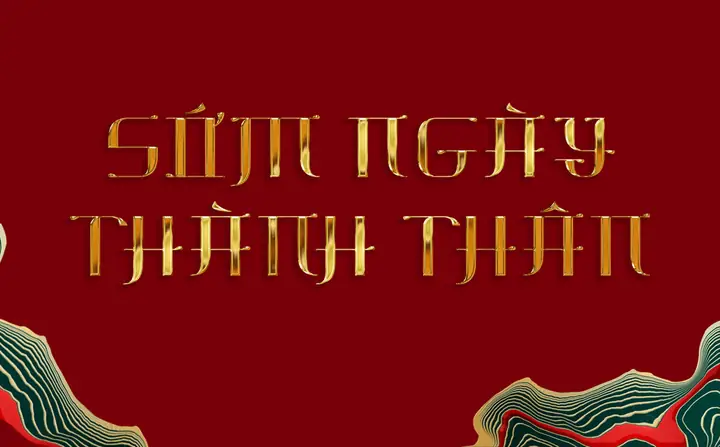
Font Lục Thư
Font Lục Thư là một trong những font chữ cổ điển nhất, mang đậm phong cách thư pháp Trung Hoa. Font này được sử dụng rộng rãi trong các thiết kế mang tính truyền thống, cổ điển. Với nét chữ mềm mại, uyển chuyển, Font Lục Thư tạo nên một vẻ đẹp tinh tế, sang trọng.
Font Hán Nôm
Font Hán Nôm là font chữ chuyên dụng cho việc gõ chữ Hán Nôm, được Việt hóa hoàn toàn. Font này rất hữu ích cho các nghiên cứu về văn hóa, lịch sử, hay đơn giản là những ai yêu thích chữ Hán Nôm. Với tính năng hỗ trợ đầy đủ các ký tự Hán Nôm, Font Hán Nôm là lựa chọn lý tưởng cho các dự án nghiên cứu, học thuật.
Font Thư Pháp
Font Thư Pháp là font chữ viết tay, mang vẻ đẹp tự nhiên và nghệ thuật. Font này được sử dụng rộng rãi trong các thiết kế mang tính nghệ thuật, sáng tạo. Với nét chữ mềm mại, tự nhiên, Font Thư Pháp tạo nên một vẻ đẹp độc đáo, ấn tượng.
Font Cổ Điển
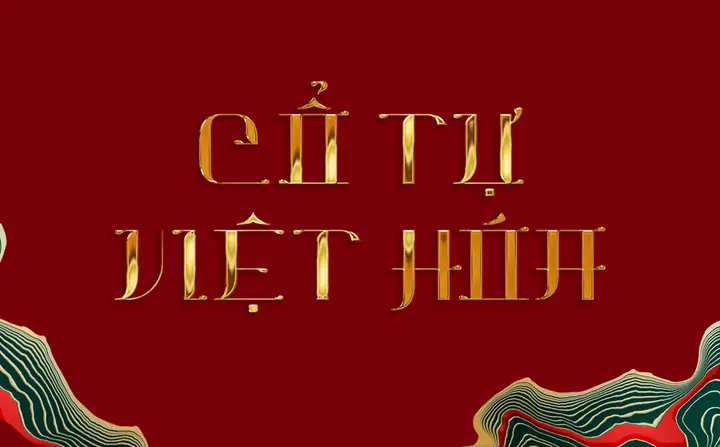
Font Cổ Điển là font chữ mang phong cách cổ điển, trang nhã. Font này được sử dụng rộng rãi trong các thiết kế mang tính lịch sử, văn hóa. Với nét chữ thanh mảnh, tinh tế, Font Cổ Điển tạo nên một vẻ đẹp sang trọng, quý phái.
Font Hiện Đại
Font Hiện Đại là font chữ mang phong cách hiện đại, trẻ trung. Font này được sử dụng rộng rãi trong các thiết kế mang tính thời đại, sáng tạo. Với nét chữ mạnh mẽ, cá tính, Font Hiện Đại tạo nên một vẻ đẹp năng động, hiện đại.
Ứng dụng của font chữ trung quốc việt hóa
Font chữ trung quốc việt hóa có rất nhiều ứng dụng trong đời sống và công việc. Dưới đây là một số ứng dụng phổ biến:
Thiết kế đồ họa
Font chữ trung quốc việt hóa được sử dụng rộng rãi trong thiết kế đồ họa, từ poster, banner, đến logo, bao bì sản phẩm. Với vẻ đẹp độc đáo, font chữ này giúp các thiết kế trở nên ấn tượng, thu hút hơn.
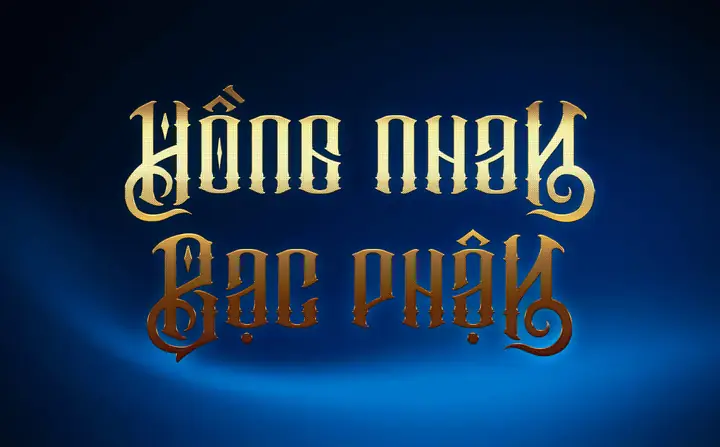
Viết thư pháp
Tổng kết
Font chữ trung quốc việt hóa là một công cụ không thể thiếu đối với các nhà thiết kế, dân văn phòng, hay đơn giản là những ai yêu thích phong cách chữ viết tay Trung Hoa. Với sự phát triển mạnh mẽ của công nghệ, việc tìm kiếm và sử dụng các font chữ Trung Quốc đã trở nên dễ dàng hơn bao giờ hết. Tuy nhiên, để có thể sử dụng font một cách hiệu quả, bạn cần hiểu rõ về các loại font, cách cài đặt, và cách sử dụng. Hy vọng rằng bài viết này đã cung cấp cho bạn những thông tin hữu ích về font chữ trung quốc việt hóa, giúp bạn có thể lựa chọn và sử dụng font một cách hiệu quả nhất. Nếu bạn có bất kỳ câu hỏi hay thắc mắc nào, hãy để lại bình luận ở phần dưới đây, chúng tôi sẽ cố gắng hỗ trợ bạn tốt nhất có thể.